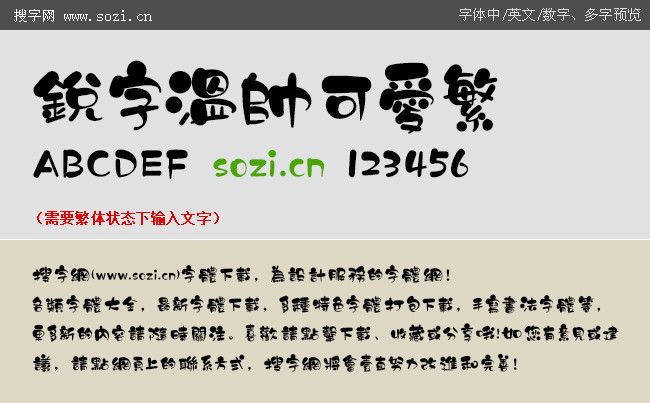
銳字溫帥可愛繁
搜字網(wǎng)提供一款銳字溫帥可愛繁中文字體下載,銳字溫帥可愛字體字形溫潤飽滿、親切乖巧,筆畫不拘一格、粗細對比協(xié)調(diào)、簡化變形有新意且不失識別性,營造了一種輕松歡快、充滿趣味性的氛圍;非常適合兒童海報,包裝設計,網(wǎng)頁設計等設計使用。【本字體供個人非商業(yè)免費使用,如需商用請聯(lián)系作者授權】